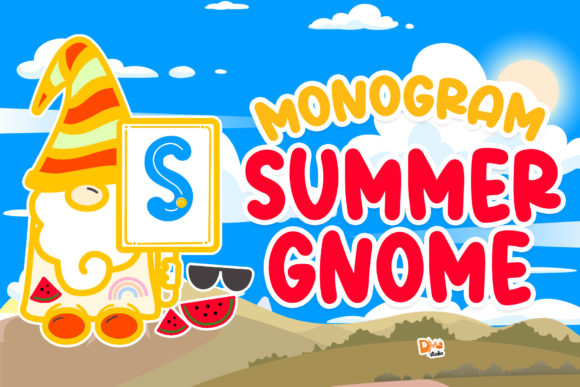
Monogram Summer Gnome - милый, причудливый и оригинальный декоративный шрифт.
Какой бы ни была тема, этот шрифт станет прекрасным подспорьем для вашей библиотеки шрифтов, так как он способен улучшить любое творение.